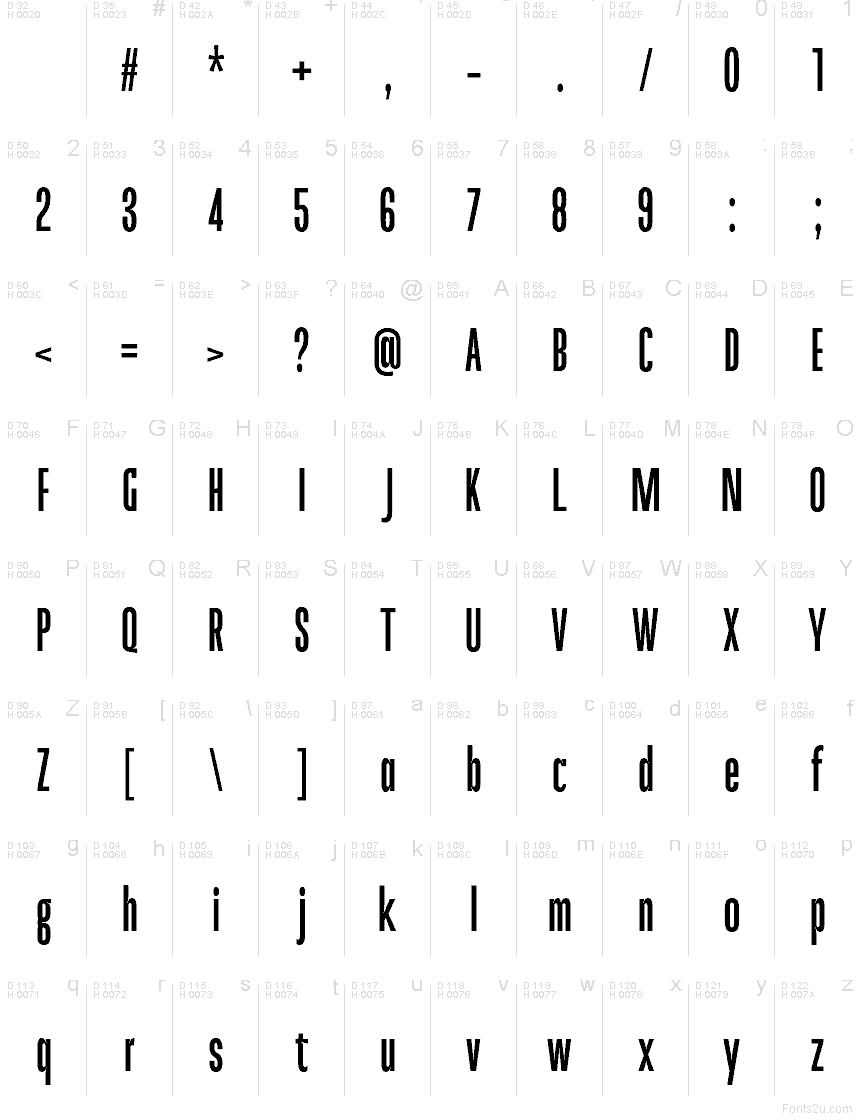
Kopile Condensed d’Afkari Studio est une police sans empattement condensée gratuite, au style vif et pensé pour l’affichage. Ses lettres hautes et serrées, alliées à des tracés francs et à un rythme vertical rigide, confèrent à cette police un aspect urbain et brut, loin du ton policé des typographies d'entreprise.
Elle s’impose partout où l’impact visuel doit rester compact : flyers musicaux, branding de cafés, étiquettes streetwear, couvertures de magazines et cartons de titres sont autant d’usages idéaux pour cette police gratuite. Grâce à ses formes étroites et affirmées, elle excelle dans les titres courts et les monogrammes, là où l’espace est limité mais où le texte doit conserver une présence marquée.